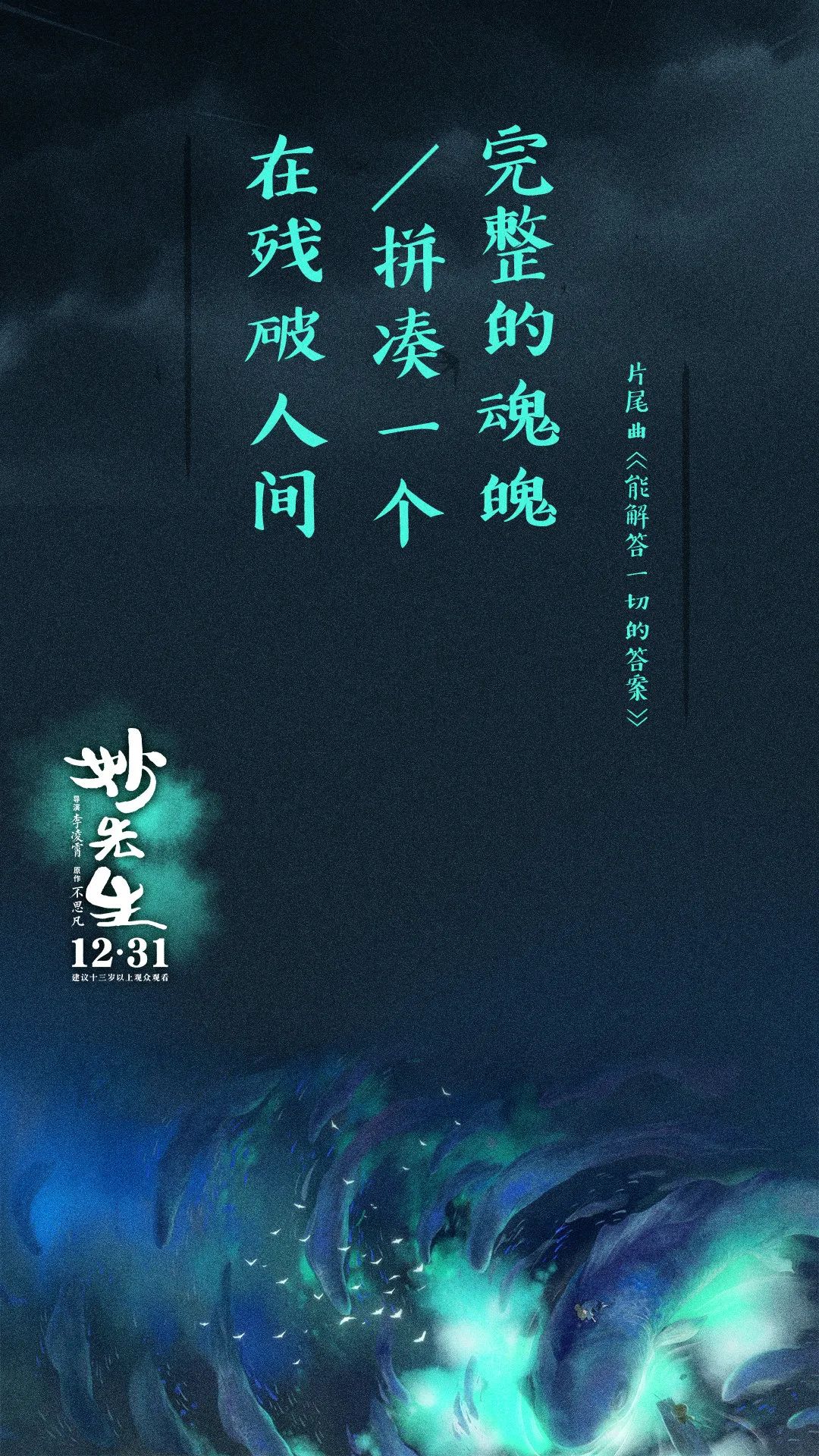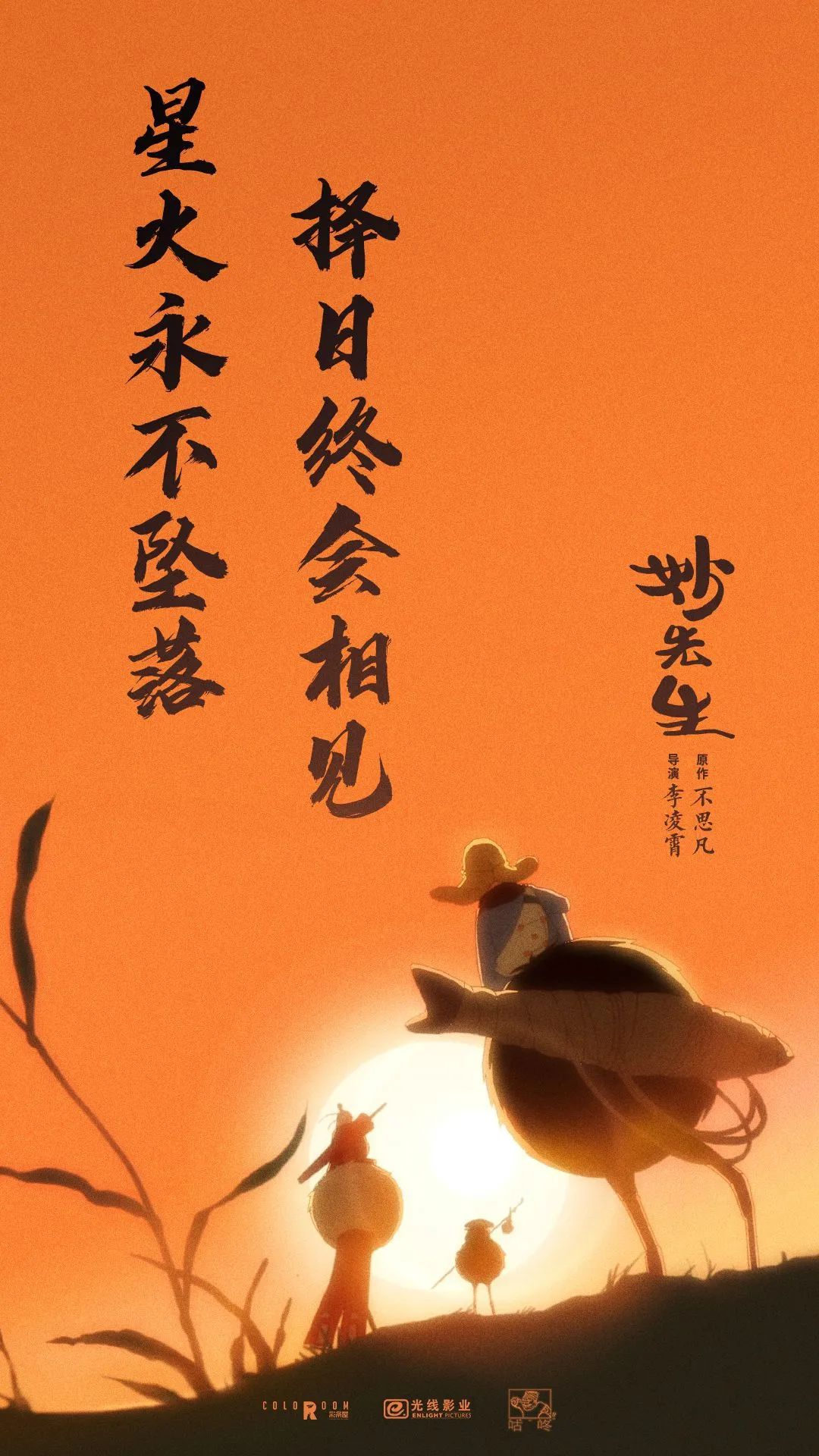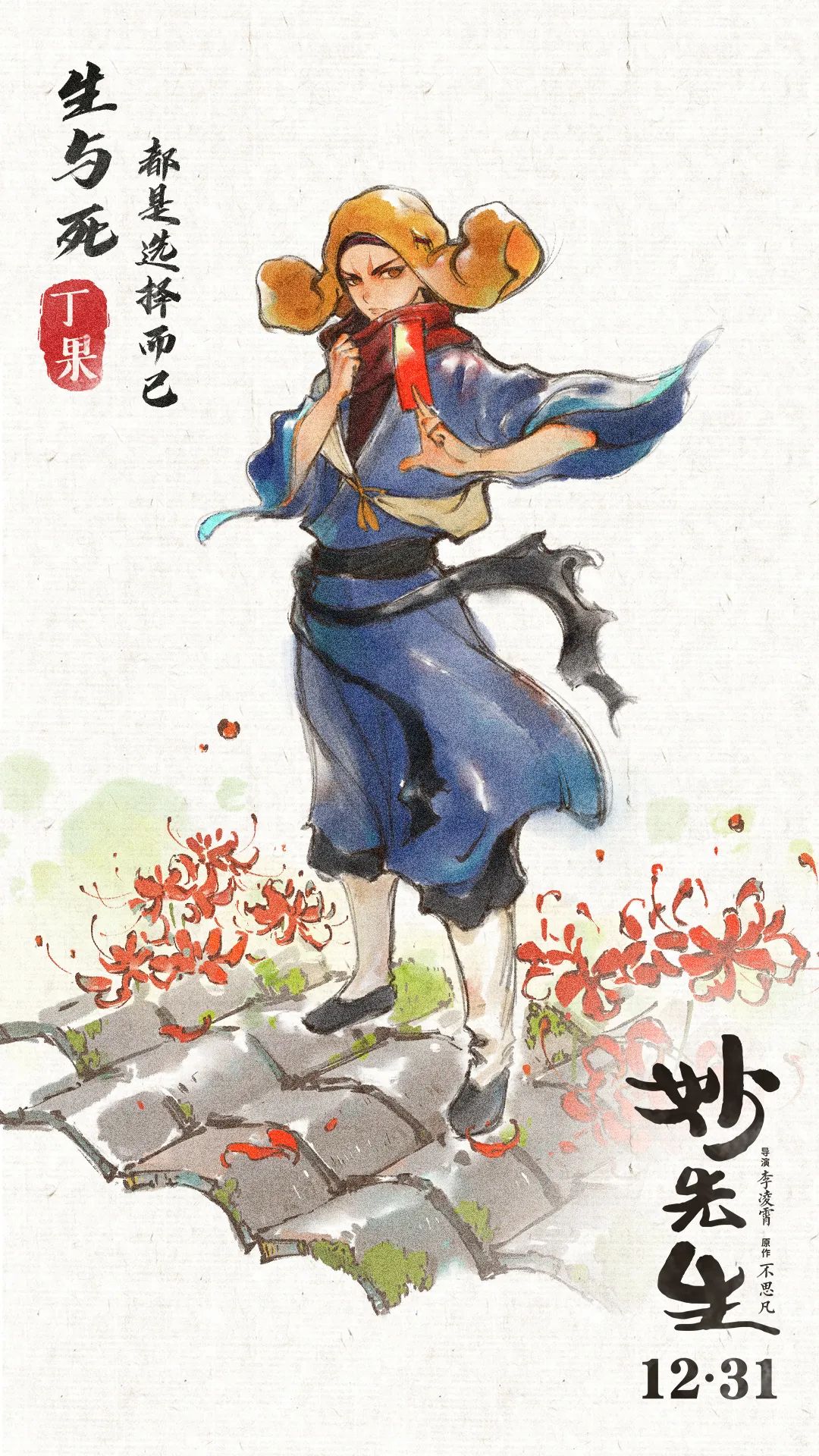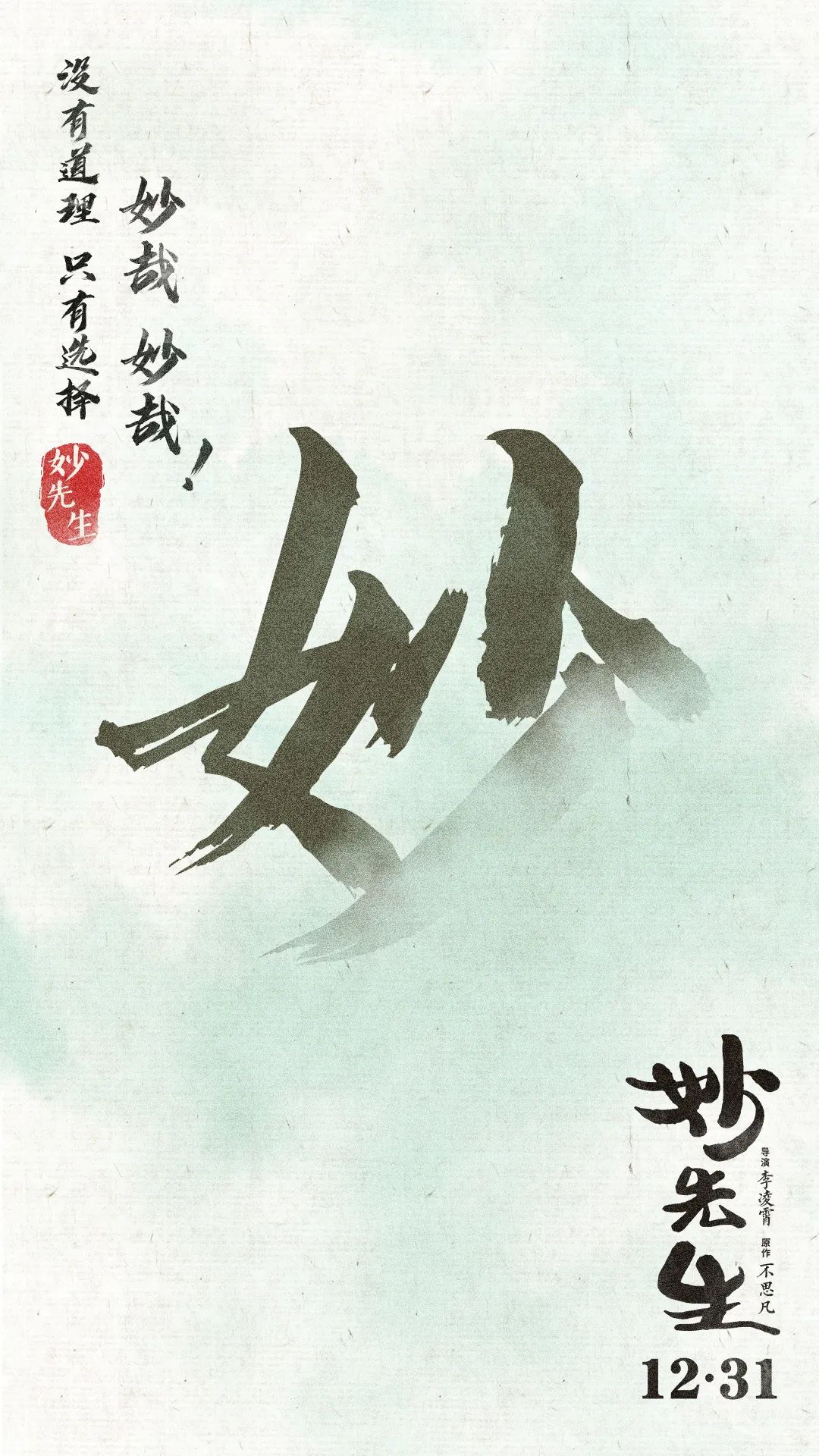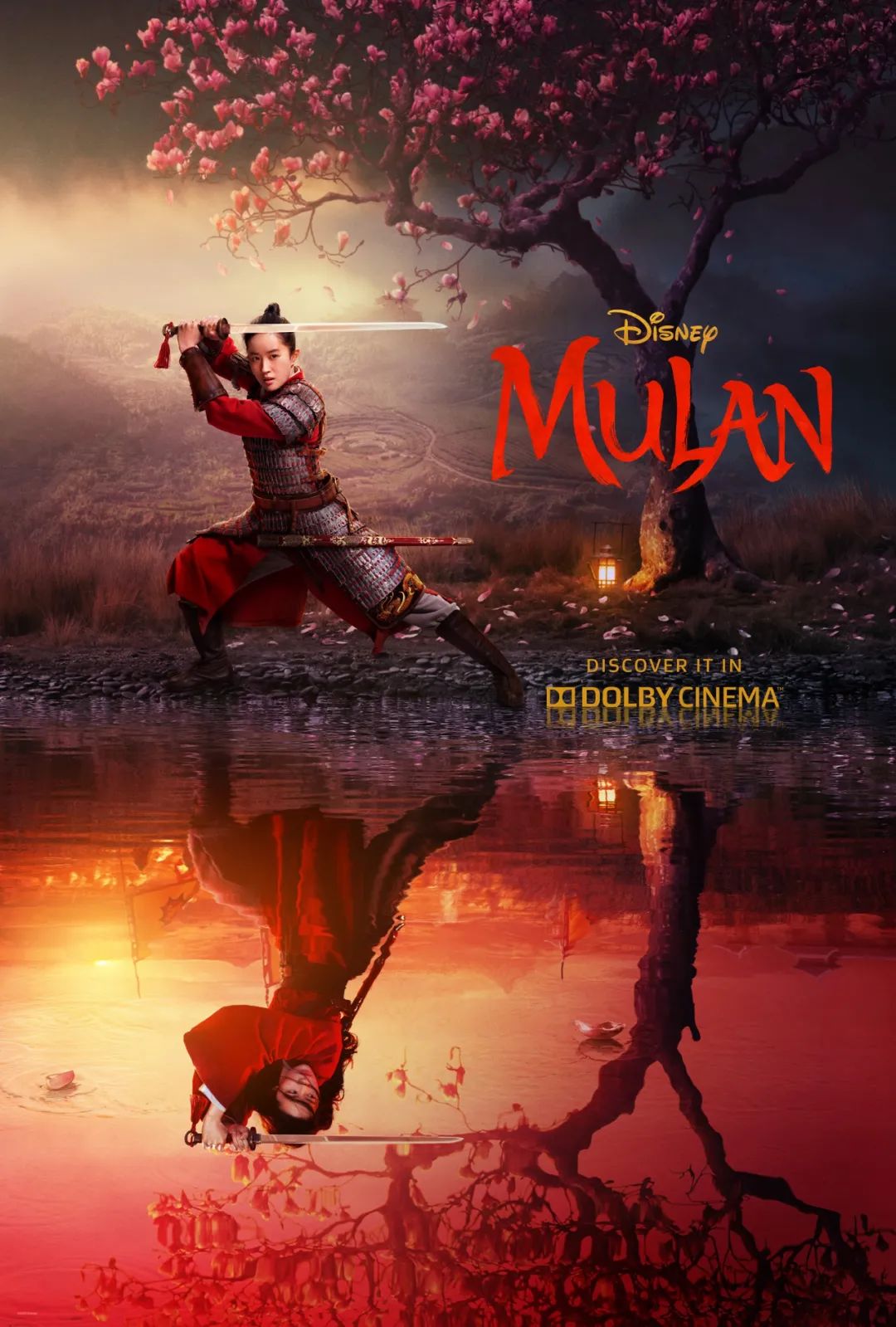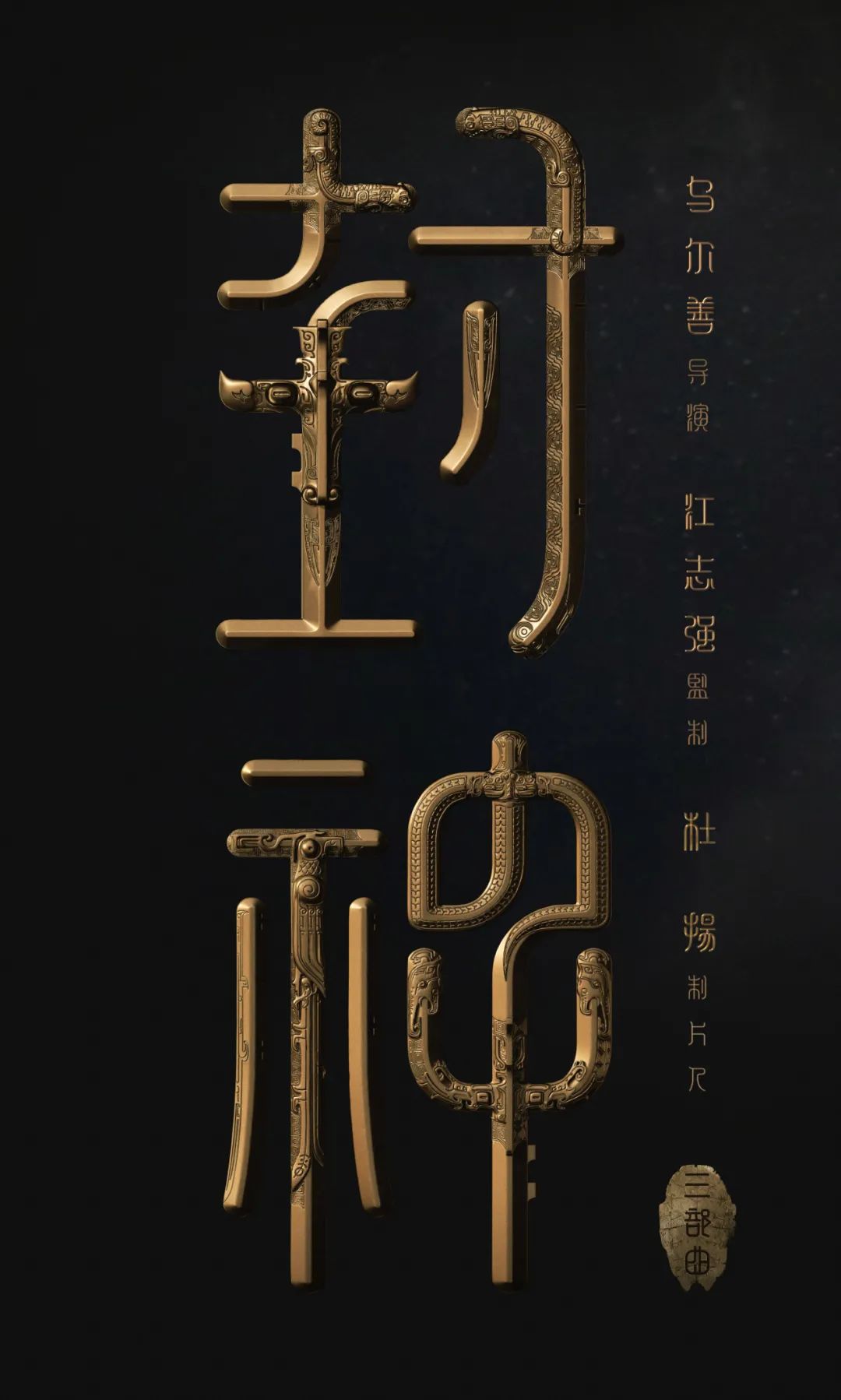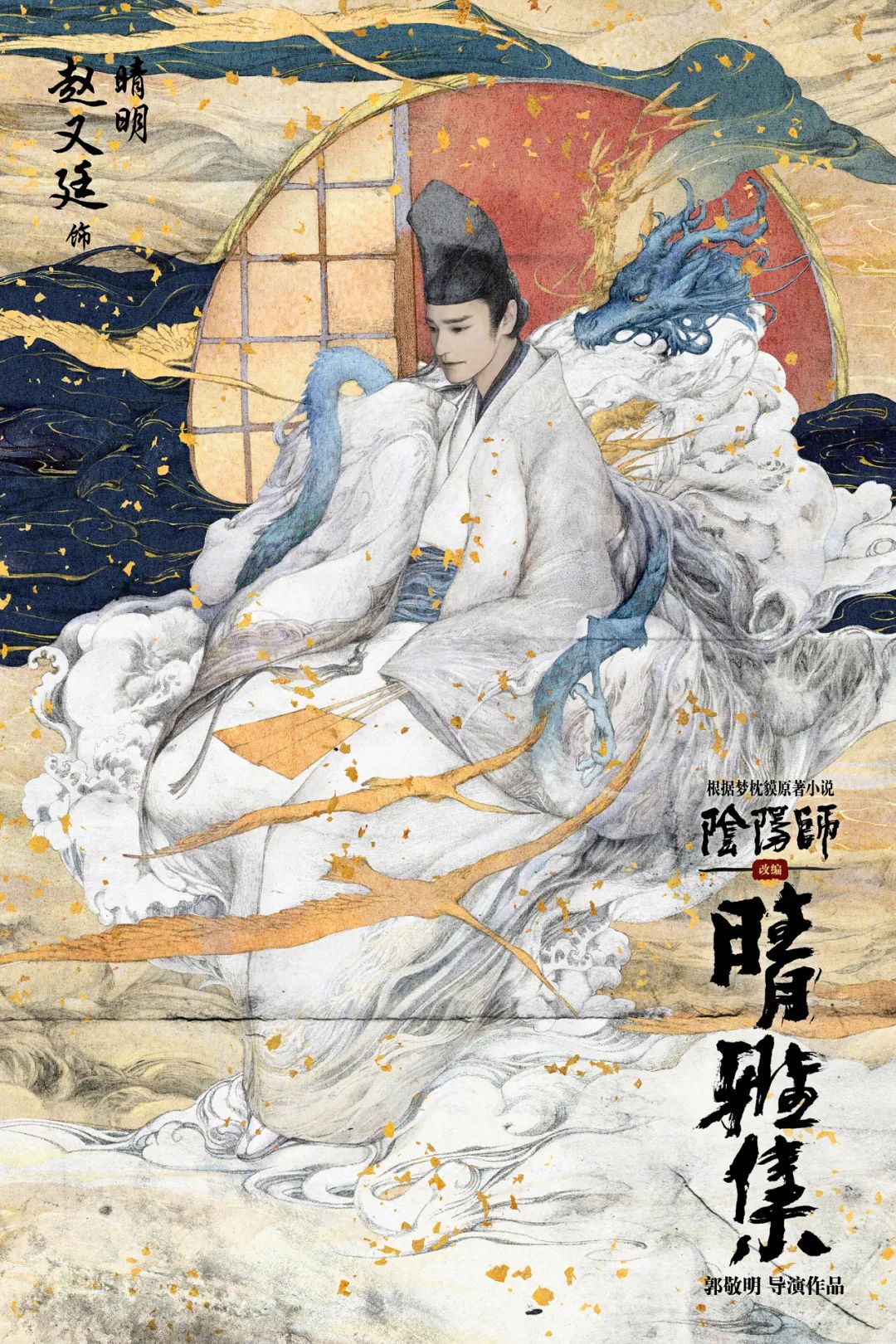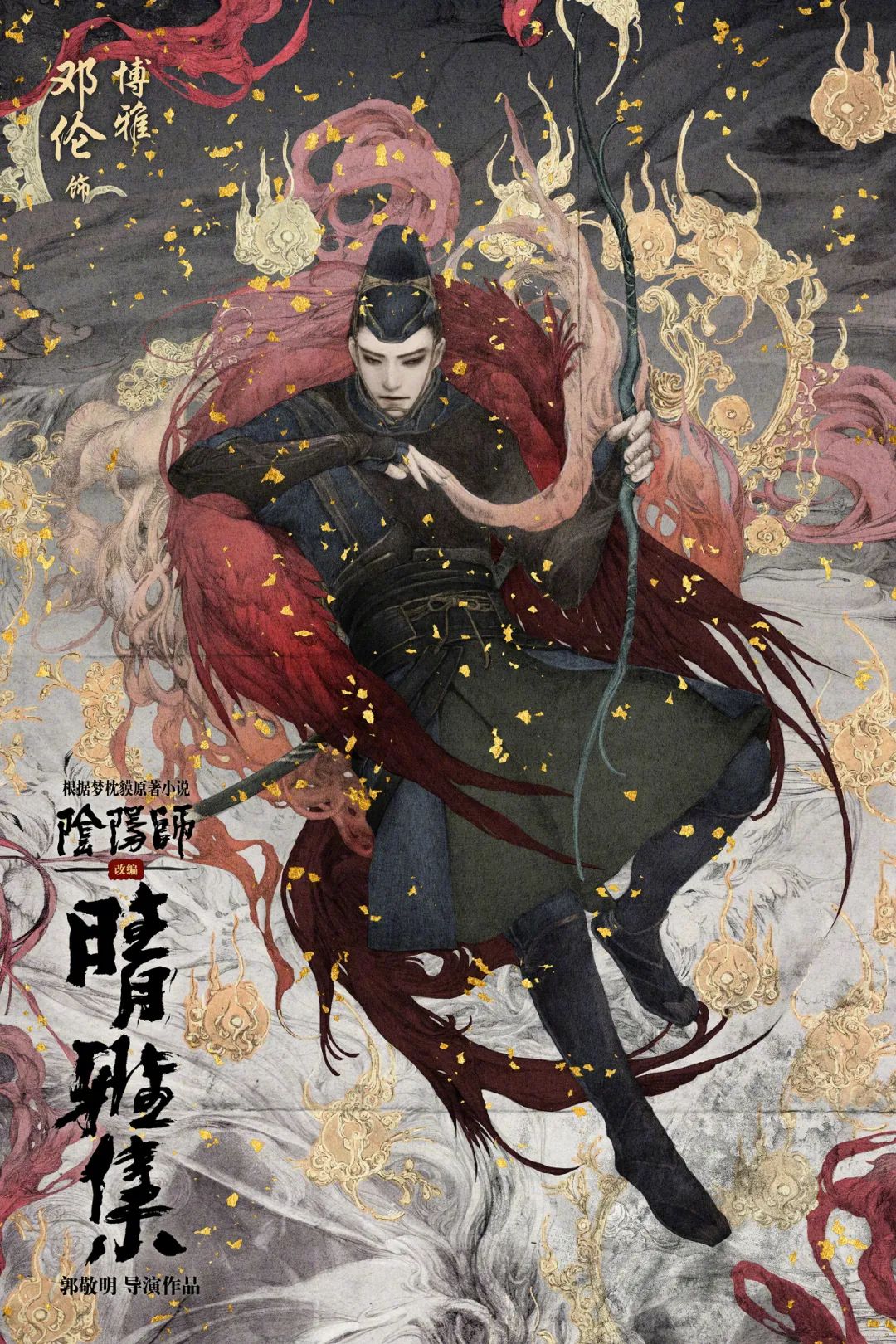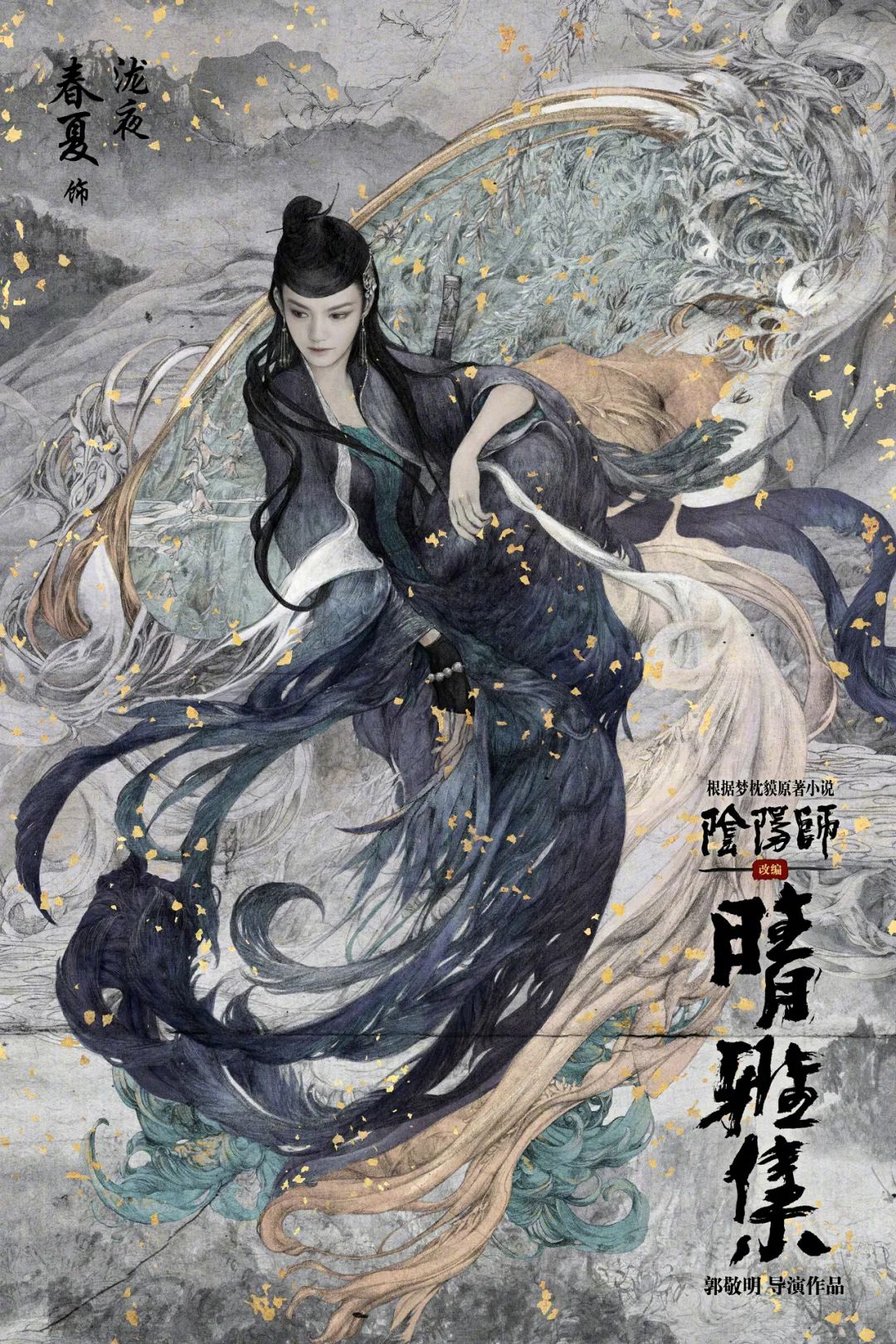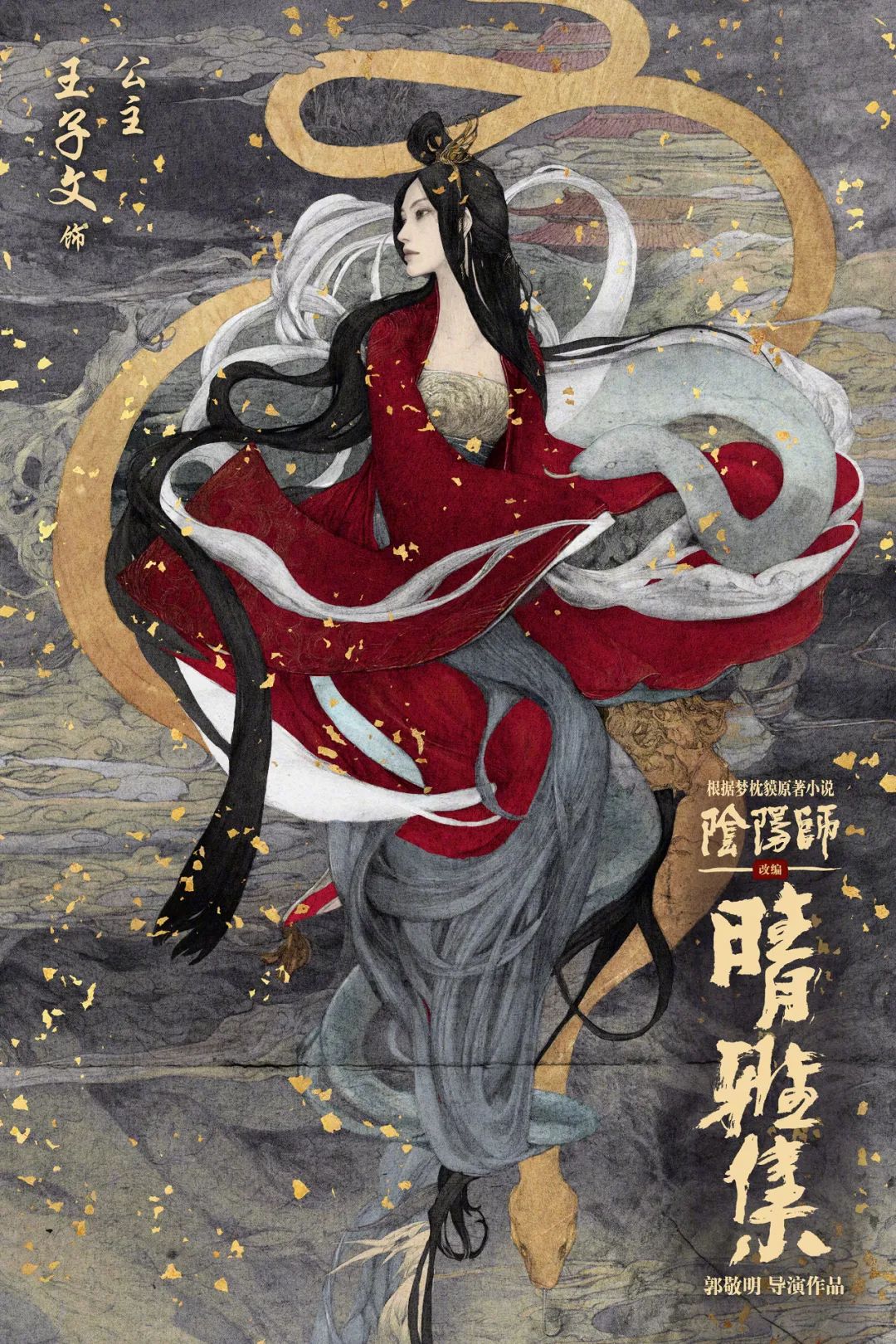
▲白舟忍者
▲庞门正道粗书体
妙先生
首先是成人动画《妙先生》,还记得这张撤档海报吗?
▲汉仪迪升英雄体
今天它终于定档7.31了,海报很有国漫风。
跟大护法的联合海报也很惊艳!
台词、歌词的海报中,选用了很有意境的汉仪新蒂唐朝体。
▲汉仪新蒂唐朝体
单人角色海报则用了很有个性的汉仪迪升英雄体,妙哉~
▲汉仪迪升英雄体
花木兰
这是柚子最期待的电影,只是还没确定上映时间,先看看海报过干瘾吧!
英文字体的设计,既也也有张扬的笔触,也有圆润的线条。
匹配的中文字体,并没有很突兀。
配合水墨海报,很是中国风。
还有日韩版本的海报,向来别有一番风味。
封神三部曲
光看海报就知道这部电影有多震撼了,每一张都是一个故事(你细品),快快定档吧!
字体设计相当精妙,像是神器拼成的。
里面的演员更是多到你认不过来……
晴雅集
还有一部电影的海报能跟封神媲美,那就是郭敬明的《晴雅集》,希望到电影院也能看到这么美轮美奂的画面。
风犬少年的天空
最后这部电影纯靠海报吸睛,特别是字体设计,简直玩出了花,刚开始满版,还算有动漫的气质。
之后画风一转,大量的飞白,不走寻常路……
跟人物的结合也很有意思,感觉要破框而出,气质、动感都有了……